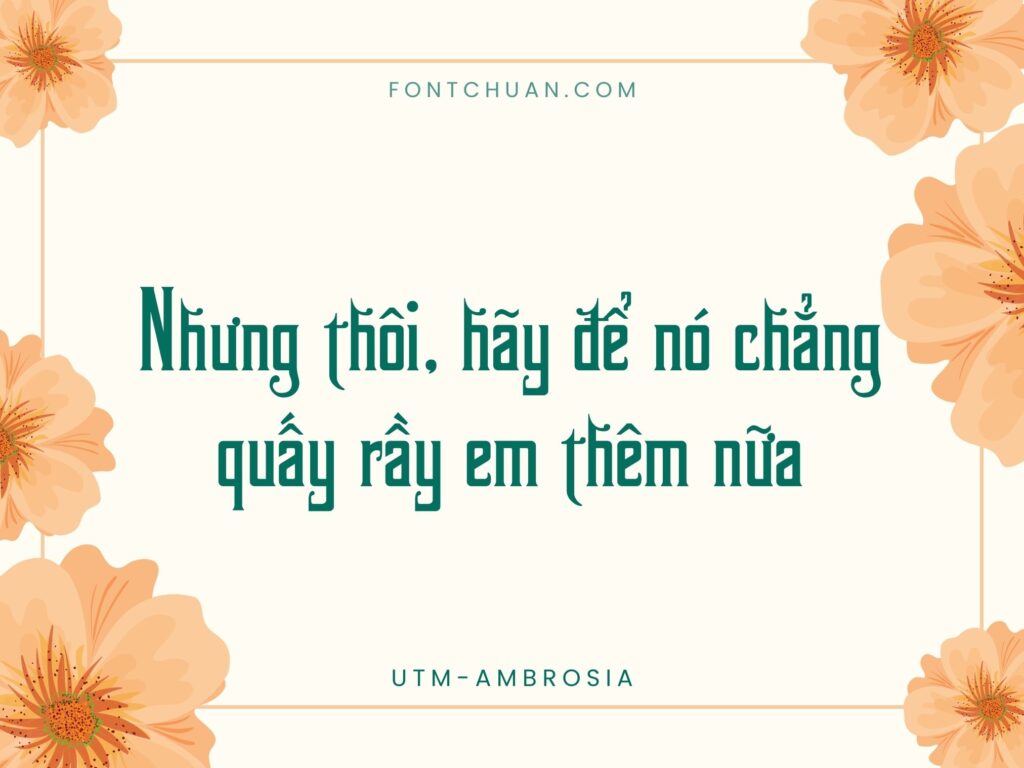
Font UTM Ambrosia Việt Hóa
UTM Ambrosia là một kiểu chữ trang trí độc đáo, thuộc nhóm Font Decorative, được thiết kế bởi Công ty TNHH Vitoen. Font này mang phong cách cổ điển với các đường nét tinh tế, tạo nên sự sang trọng và thu hút. Phiên bản này đã được Việt hóa, hỗ trợ đầy đủ tiếng Việt cùng hơn 200 ngôn ngữ khác. Thành viên của Font Chuẩn đã sưu tầm và chọn lọc font này nhằm đáp ứng nhu cầu đa dạng của bạn đọc và ứng dụng thực tế vào các dự án thiết kế.
UTM Ambrosia có cấu trúc chữ với các nét thanh mảnh và uốn lượn mềm mại, tạo nên vẻ đẹp nghệ thuật và cổ điển. Font này phù hợp cho các ứng dụng như thiết kế logo, tiêu đề, bao bì sản phẩm và các ấn phẩm in ấn yêu cầu sự sang trọng và tinh tế. Các ngành nghề như quảng cáo, thiệp cưới, giáo dục và ẩm thực có thể tận dụng UTM Ambrosia để tạo điểm nhấn độc đáo trong thiết kế.